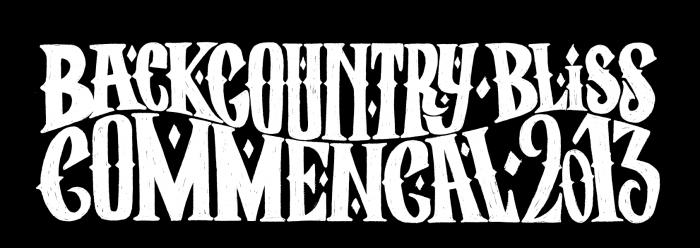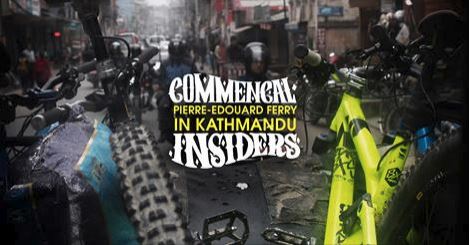
Suche Schriftart aus Beispielbild
Suche die Schriftart des Schriftzuges "Commencal, Insiders".
Die Wellenform ist wahrscheinlich manuell per Photoshop erzeugt suche lediglich die Schriftart!
Hier noch ein paar Buchstaben mehr …
Würde mal annehmen, das derartiges schneller und einfacher komplett zu zeichnen ist, als  zuerst die Schrift zu verwenden und das dann derart hin zu zupfen.
sieht für mich auch handmade aus – möglicherweise irgendeiner «western»haften schrift nachempfunden (leathercrafter, sergio fy, yuma etc.).
@catfonts mir geht es in erster Linie um die Schriftart (oder ähnliche).
Das 1 zu 1 so hinzubiegen ist erstmal Nebensache ;)
@Norbert: Danke für deine Vorschläge! Das geht schon in die Richtung wie ich mir das Vorstelle!
Allerdings sind mir diese Western Fonts alle zu "Cowboy" mäßig ;)
Finde ja die Schriftart aus dem Beispielbild geht mehr in die Richtung Western+Magier.
DavidsonAmericana – die ist zwar grundsätzlich anders, hat aber auch diese „Western-Magic-Zackel“
das wäre doch mal ein anlass, eine neue schriftenliste »western-look« anzulegen, oder?
ich hätte da folgende kandidaten:
ironmonger
barnum block
cottonwood
greenwood
ironwood
mesquite
nashville
pepperwood
playbill
ponderosa
rosewood
thunderbird
zebrawood